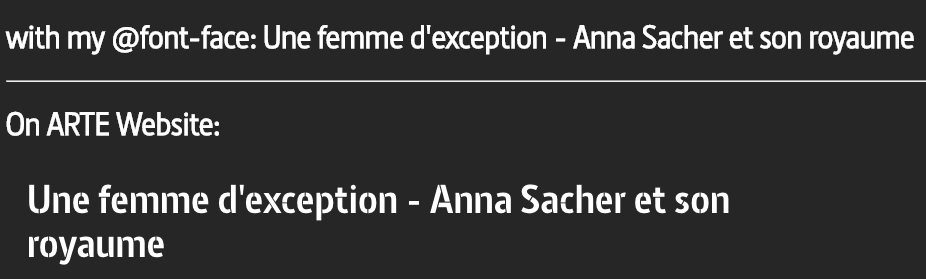
Le site d'Arte utilise Barna Stencil (voir le titre "une femme d'exception").
Je ne comprends pas pourquoi le woff apparait differement chez moi quand j'intègre le @font-face dans une page html.
merci de ta promptitude Raphaël, oui même path, et cursive ne change rien… si tu regardes la capture dans le premier post, tu peux voir que barna se charge bien dans mon @font-face mais il manque les stries (petit sillons) dans les lettres.
C'est peut-être un problème dans le fichier de police. Tu as essayé de le récupérer à partir d'une autre source ?
oui depuis les premières lignes de la feuille, c'est bien la première fois que j'ai un conflit avec woff/woff2. A moins qu'ils utilisent js pour "injecter" cet effet ?